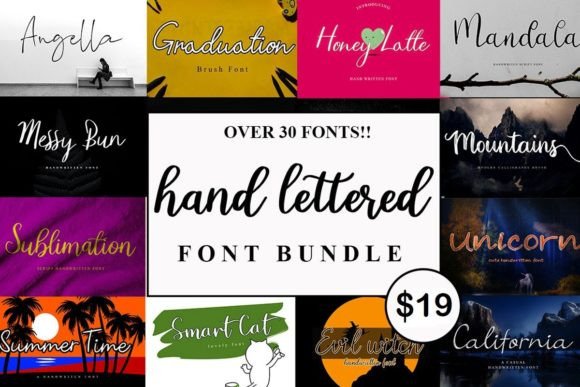
Handlettered Font Bundle
Se stai cercando risorse di alta qualità come Handlettered Font Bundle, questo pacchetto premium è una scelta fantastica per i tuoi progetti creativi.